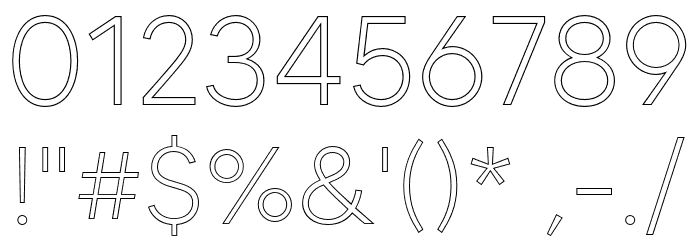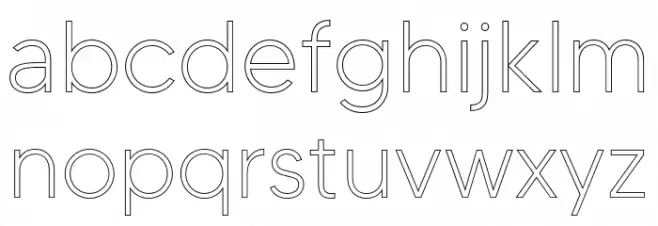
MADETOMMYOutline-Light Font
| Famiglia di caratteri | MADE TOMMY Outline |
| Progetti proposti | Ideal for branding, logos, headlines, and modern design projects where a sleek and minimalistic look is desired. |